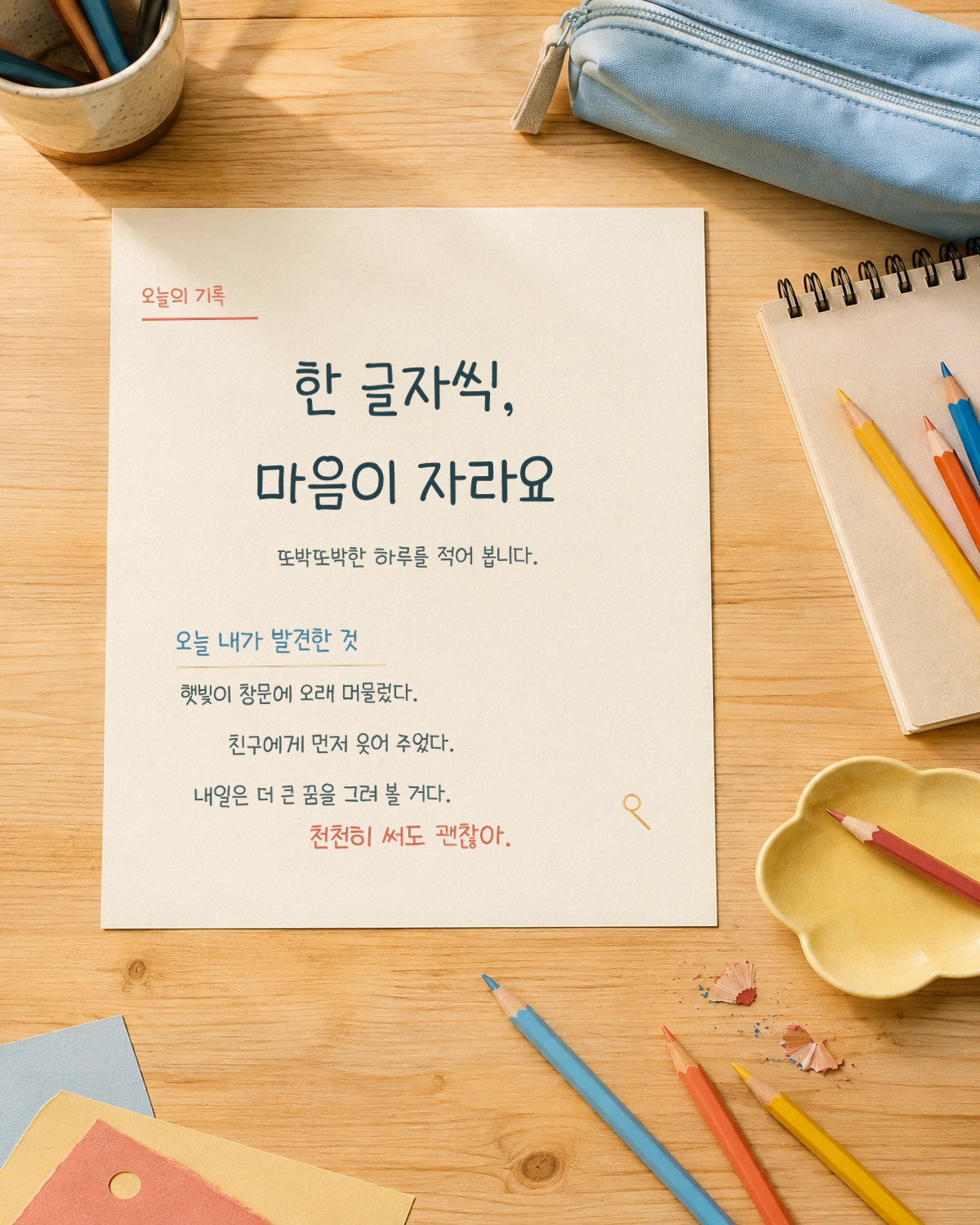
교보손글씨 2019 — 교보문고에서 배포하는 무료 폰트입니다. 손글쓰기대회 아동부문 으뜸상을 받은 열두 살 어린이의 글씨를 그대로 옮긴 정감 어린 손글씨체
교보문고가 해마다 여는 교보손글쓰기대회에서, 2019년 제5회 아동부문 으뜸상을 받은 열두 살 어린이의 손글씨를 그대로 서체로 옮긴 글꼴입니다. 그해 응모작 6,298점 가운데 뽑힌 글씨이고, 서체 개발은 윤디자인그룹이 맡아 약 석 달에 걸쳐 진행했습니다. 2020년 4월에 무료로 공개됐습니다.
개발팀이 밝힌 작업 방향은 원래 글씨의 특징을 살리면서 가독성을 보완하는 것이었습니다. 구체적으로는 모든 글자 폭을 가변으로 디자인해 손으로 쓸 때 생기는 들쭉날쭉한 리듬을 남겼고, 획의 시작과 끝을 둥글게 처리해 사인펜의 잉크 뭉침을 표현했습니다. 원래 글씨를 쓴 필기구가 사인펜이었다는 뜻입니다. 파일에서 재어 보면 받침이 붙을 때 글자가 0.15em쯤 더 아래로 내려가는 탈네모틀 구조라, 글줄이 기계적으로 정렬되지 않고 손글씨처럼 흔들립니다.
굵기는 하나뿐입니다. 교보문고는 인쇄물과 웹, 모바일, 광고물, 영상 자료까지 폭넓게 쓸 수 있다고 안내하고 있고 실제로 영상 자막에서 자주 보입니다. 어린이 손글씨가 바탕이라 정감 있는 자리에서 힘을 내는 대신, 공문이나 금융·의료 안내처럼 신뢰감이 먼저인 곳과는 성격이 맞지 않습니다. 폰트 파일을 고치거나 다시 배포하는 것은 금지돼 있으니 내려받을 때는 교보문고 공식 페이지를 이용하세요.